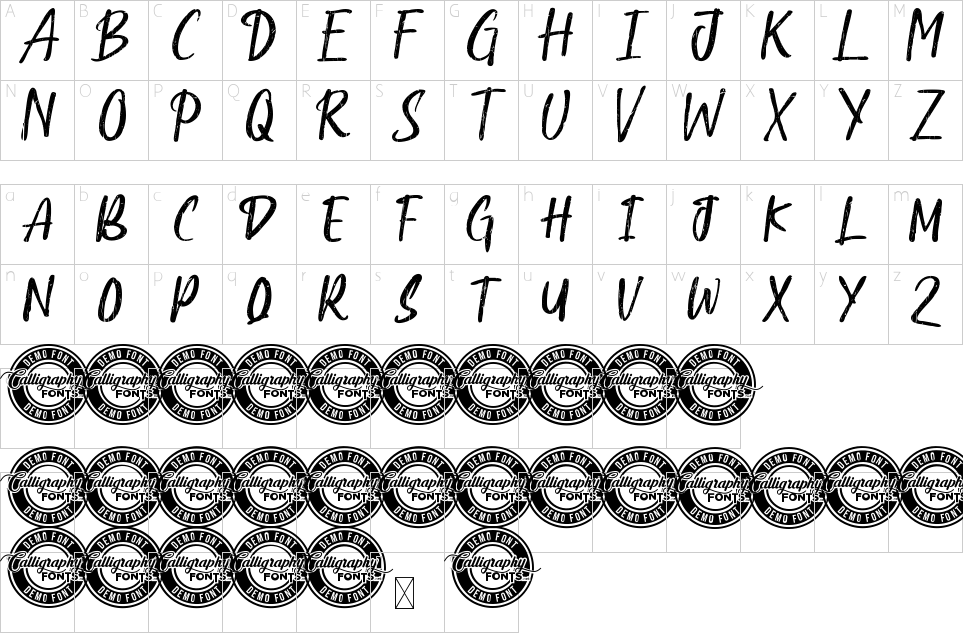
A fonte Jungle Queen é uma elegante escolha para designers e criativos do Brasil, especialmente aqueles interessados em adicionar um toque de natureza às suas criações digitais. Desenvolvida pela equipe de CalligraphyFonts, ela incorpora influências da flora e fauna da selva tropical, criando um estilo que reflete a vitalidade e a diversidade das matas. Esta fonte, disponível tanto para Windows quanto para Mac, é perfeita para aplicativos de design gráfico, editoriais de blogs e até mesmo para personalizar suas próprias mensagens online, oferecendo um contraponto sofisticado às letras mais convencionais. Com seu design cuidadosamente cuidado, Jungle Queen é uma excelente adição para quem busca uma fonte única e versátil para suas próximas projetos. A fonte tem sido adotada por muitos criativos, sendo baixada mais de 1.988 vezes, o que mostra o seu valor e popularidade.